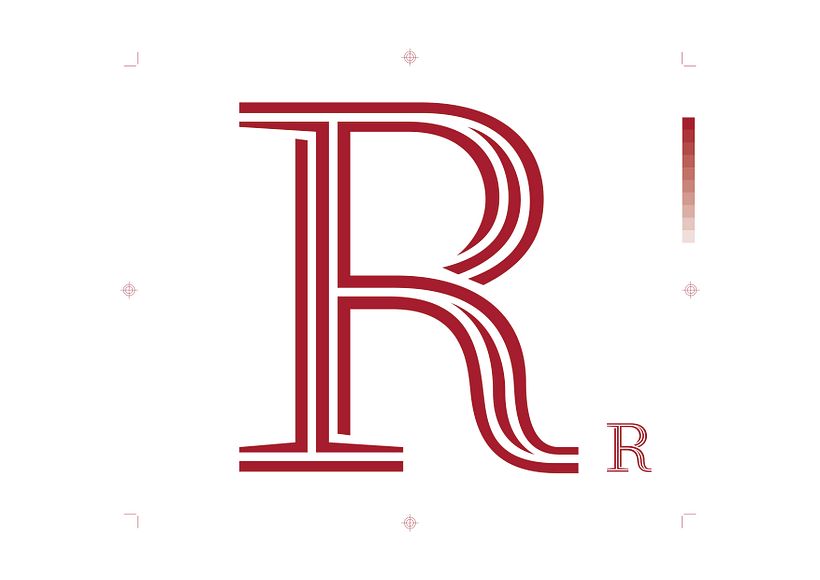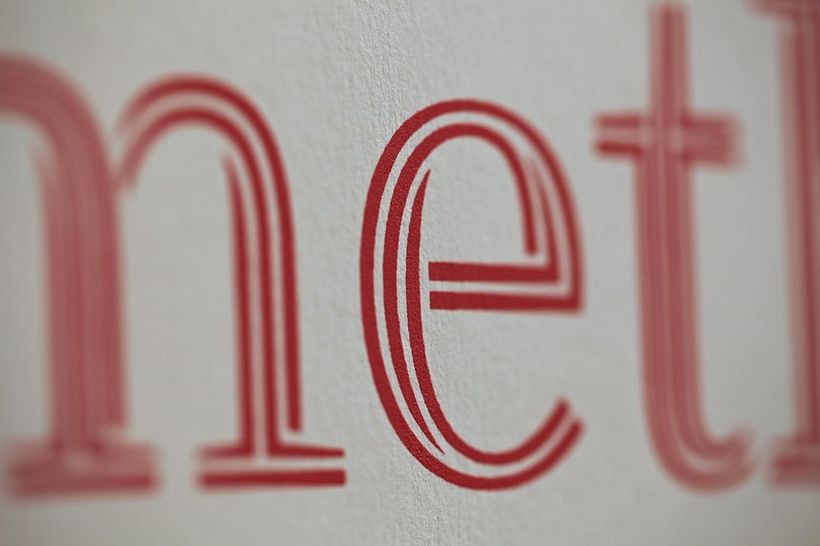
La primera tipografía 100% sustentable
La sustentabilidad, es una característica que todos los diseños de hoy en día buscan obtener. Su significado es muy poderoso, ya que va de la mano con el usar menos para tener más. Así que la tipografía diseñada por Dan Rhatigan, es un recurso tipográfico que muestra de manera creativa, como a través de una simple tipografía uno puede llegar a ser sustentable.
Ryman Eco es el resultado de analizar la cantidad tan grande que se usa de tinta para la impresión de ciertas tipografías y los costos que genera. En los cuales por ejemplo, van de la mano industrias químicas (en la fabricación del papel y la tinta) hasta las editoriales, quienes en conjunto representan los más beneficiados por esta tipografía.
Por supuesto que Dan no busca que esta tipografía sea LA solución a los grandes problemas ambientales del mundo, pero si ser parte importante de la conversación que se genera, al hablar de reducir recursos para salvar al planeta.